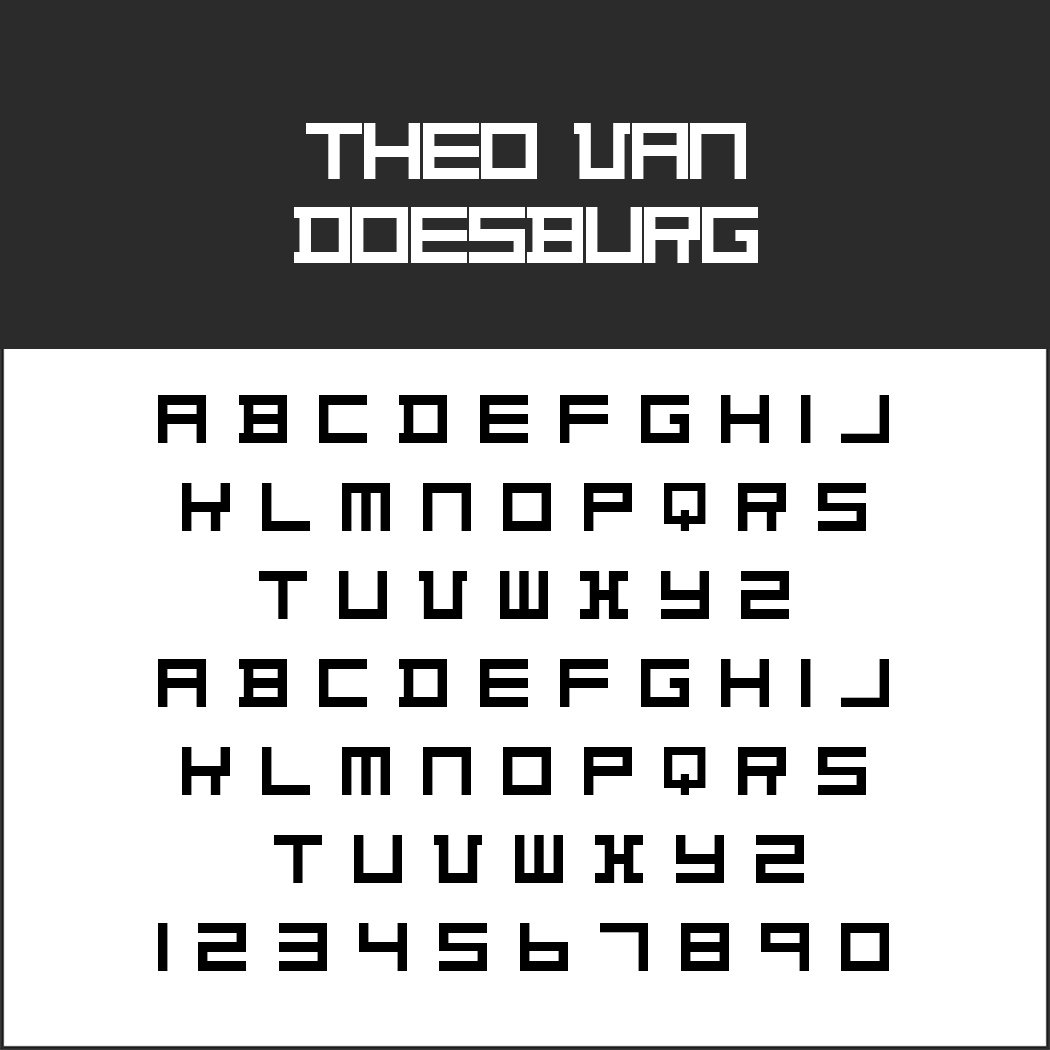
So golden wie in späteren Jahrzehnten verklärt, waren die 1920er Jahre allenfalls während einer sehr kurzen Zeitspanne und nur für die finanziell abgesicherte Oberschicht. Der Mythos der überbordenden Lebensfreude hält sich jedoch hartnäckig und nährt das Interesse an dieser Epoche. In Wirklichkeit war es eine Zeit großer Umwälzungen, was sich auch in der Schriftart 20er Jahre bemerkbar macht. Da existiert Antiquiertes neben nie Dagewesenem.
Schriftart 20er Jahre: AvignonAvignon
Die moderne, serifenlose Schrift entstand 1920 für eine Werbung. Auffallend sind die markanten Kleinbuchstaben und die niedrigen Unterlängen.
Schriftart 20er Jahre: Boogie Nights NF
Für diesen Font ließ sich der Designer von einer Schrift inspirieren, die auf einer österreichischen Handelsmesse zum Einsatz kam. Wir haben die Shadow-Version abgebildet, es gibt Boogie Nights NF aber auch in massiver Ausführung.
Schriftart 20er Jahre: GANGUE OUAISGangue Ouais
Mit seinen einprägsamen Großbuchstaben und den kleinen Versalien zieht Gangue Ouais die Aufmerksamkeit auf sich. Der kanadische Designer möchte den Namen als „Gangway mit französischem Akzent“ ausgesprochen wissen.
20er Jahre Schrift: Grenadier NF
Dieser Font verbreitet den Flair des Art Deco. Er basiert auf der Schrift Modernistic aus den 1920er Jahren des US-amerikanischen Typographen Samuel Welo.
20er Jahre Schrift: Kleist-Fraktur
Die 1920er Jahre standen nicht nur für den Aufbruch in die Moderne, sondern auch für die Pflege alter Traditionen. So entstanden auch viele gebrochene Schriften wie 1928 die Kleist-Fraktur aus der Hand von Walter Tiemann.
Schriftart 20er Jahre: March Madness NF
Sehr verspielt präsentiert sich March Madness NF, das auf ein italienisches Plakat aus den 1920er Jahren des Meisters Marcello Dudovich zurückgeht.
Schriftart: Materhorn NF
Der Designer nennt Materhorn NF „ein perfektes Beispiel für den Gebrauchsgraphik-Stil der 1920er Jahre„. Der Font, auch im Internet unter den Namen Fanfare oder Berlin Deco bekannt, vereint Elemente des Art Deco und Formen der deutschen Frakturschrift.
Schriftart 20er Jahre: MutterMutter
Vorlage ist das Plakat zum Stummfilm Mutter Krauses Fahrt ins Glück von Regisseur Phil Jutzi, der 1929 Premiere feierte und später verboten wurde. Rainer Werner Fassbinder drehte 1975 eine neue Fassung unter dem Titel Mutter Küsters Fahrt zum Himmel.
1920er Schrift: Nickerbocker NF
Mit diesem Art-Deco-Font orientiert sich der Designer lose an der Schriftart Gatsby.
Schriftart 20er Jahre: Oranienbaum
Ausgeprägte Serifen und starke Kontraste: Diese Bodoni-Schrift ist durch ihre Charakteristika typisch für Schriften im ersten Viertel des 20. Jahrhunderts. Sie eignet sich sowohl für Überschriften als auch längere Fließtexte.
Schriftart 20er Jahre: Riot Squad NF
Das Wechselspiel aus dünnen und starken Strichen sowie die schwungvolle Unbekümmertheit machen den besonderen Charme von Riot Squad NF aus.
1920er Schrift: Speedball No 3 NF
Die US-amerikanische Manufaktur Speedball veröffentlichte 1915 eine Broschüre mit Schriftarten, um ihre Füller besser zu vermarkten. Daraus stammt auch die Vorlage zu diesem Font.
Schriftart 20er Jahre: StageStage
Der Name ist Programm: Bühne frei für einen Font, der die lebensbejahende Seite der 20er Jahre, die Feierfreudigkeit und den Genuss neuen „Amüsemangs“ betont.
Schriftart 20er Jahre: Tex Gyre Schola
Mit Tex Gyre Schola imitieren die Designer die Century Schoolbook von Morris Fuller Benton aus dem Jahr 1919, die gut zum 20er-Jahre-Stil passt.
Schrift: Theo van Doesburg
Der Niederländer Theo van Doesburg begründete die Künstlerbewegung De Stijl mit. Der gleichnamige Font geht auf seine Entwürfe aus dem Jahr 1917 zurück.